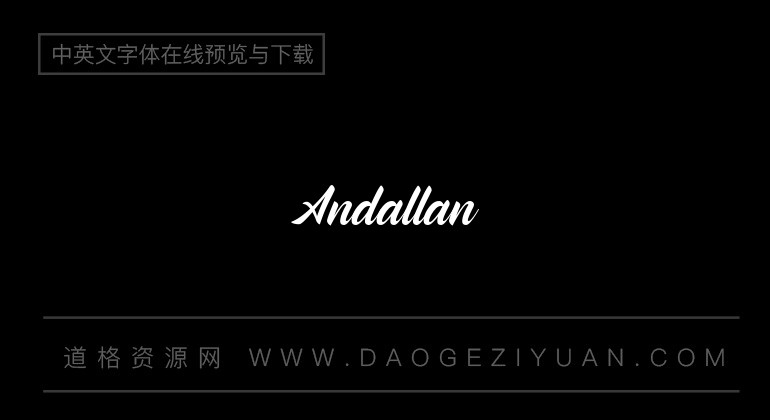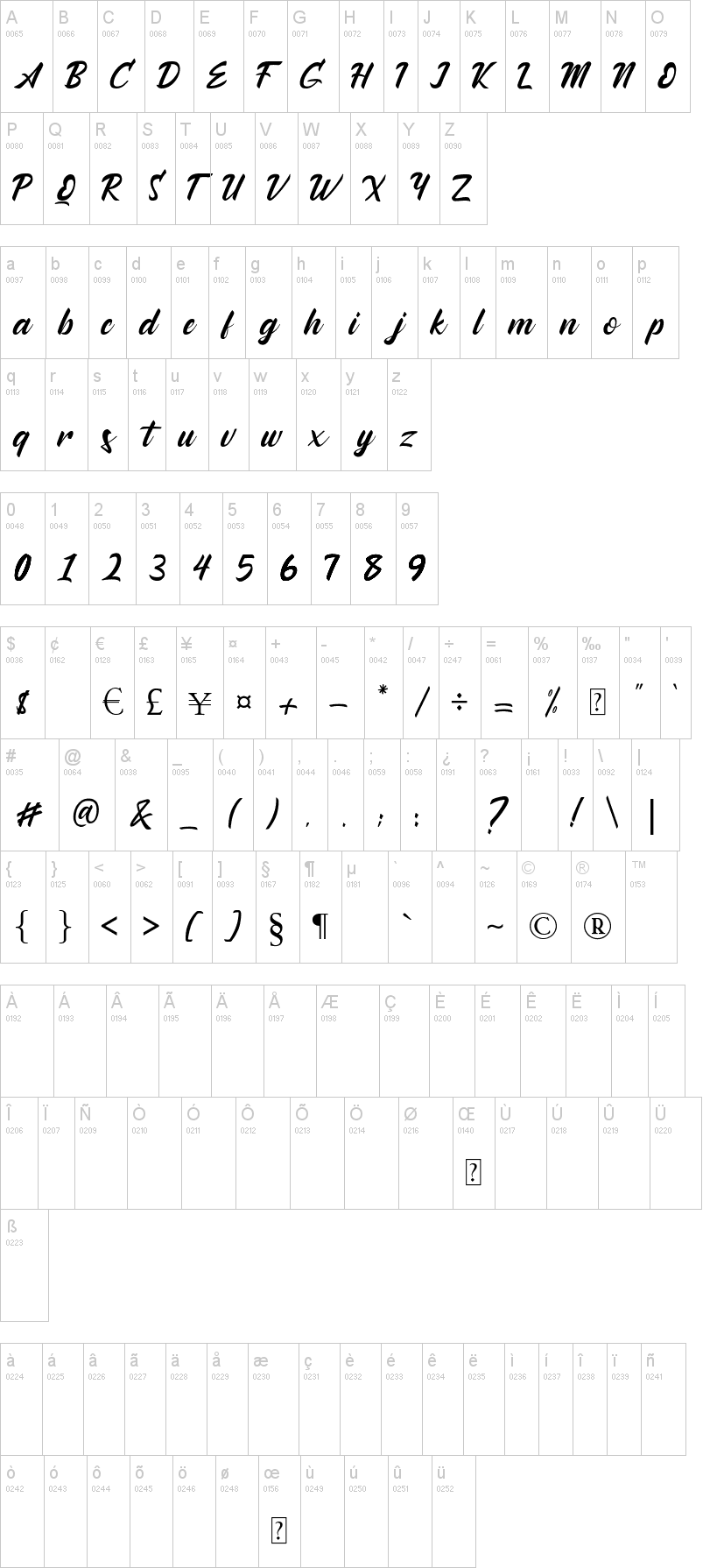
Andallan
Andallan 字体是一种漂亮、优雅的手写风格字体,其特点是流畅的线条和圆润的笔画。该字体由设计师 Mans Greback 所创建,于 2019 年发布。Andallan 字体有两种版本:Andallan Regular 和 Andallan Bold。它们都具有相同的手写字风格,但是 Bold 版本更加加粗和突出。 Andallan 字体非常适合用于设计优雅的品牌标志、包装设计、海报、印刷品、名片和其他宣传材料。它的设计风格适用于多种风格和主题,比如时尚、美容、婚礼、旅游、餐饮等。Andallan 字体是一种非常实用的字体,值得设计师们尝试使用。
Andallan是一款非常不错的手写艺术字体,具有很好的视觉感,适合于文化类的宣传设计、商业类品牌的广告和产品包装设计以及个性化文字排版等较多场景。